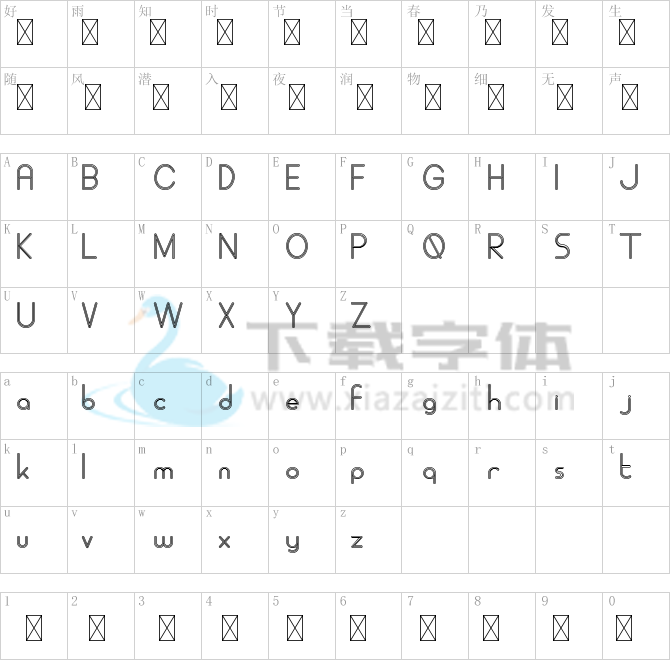
ALDORA DEMO Stroke.ttf字体下载,这款字体结构工整、笔画清晰,兼顾美观与易读性,适用于标题、正文、海报、包装、LOGO 等多种场景。字形优雅稳定,风格百搭耐看,适配日常排版与创意设计,让文字呈现更舒适、更具质感。ALDORA DEMO Stroke.ttf字体下载一笔一画,皆是细节,以均衡的比例、流畅的线条打造舒适视觉体验,字形端正大气,风格简约现代。无论是商业设计、品牌宣传还是日常排版,都能轻松驾驭,让文字更有格调与力量。ALDORA DEMO Stroke.ttf字体下载字体下载。